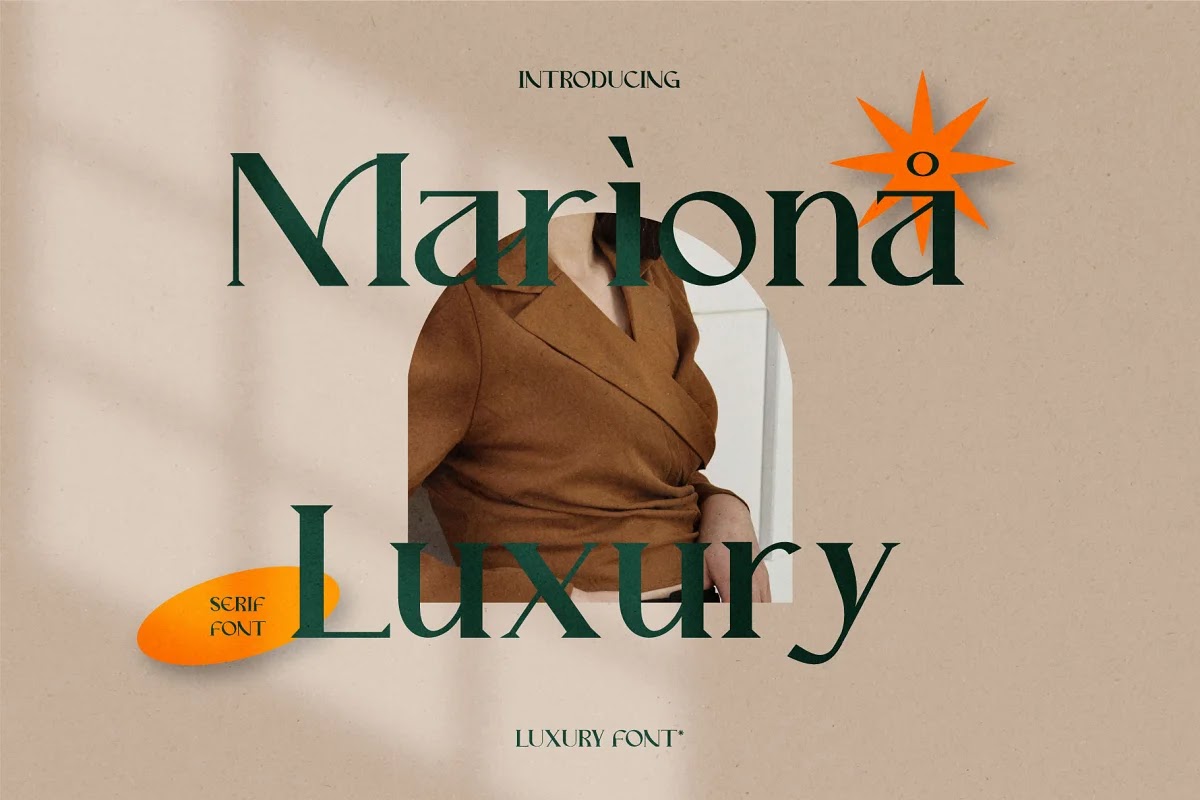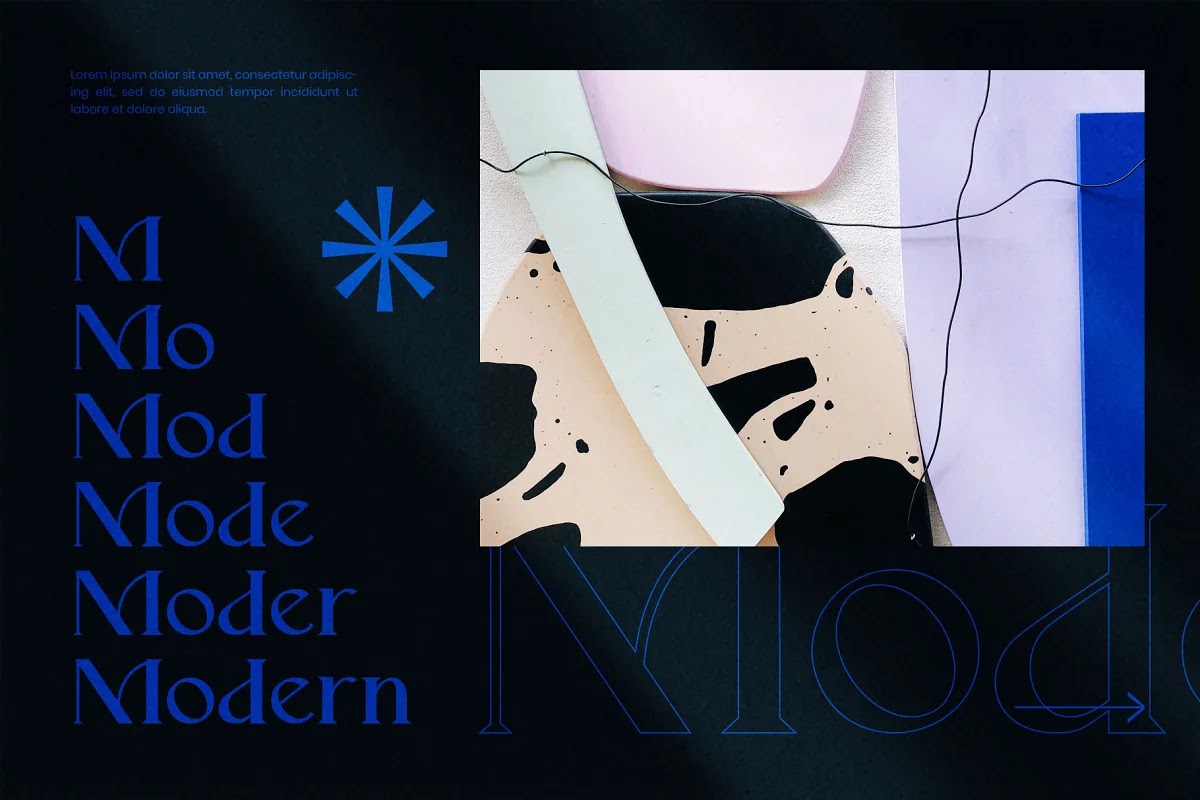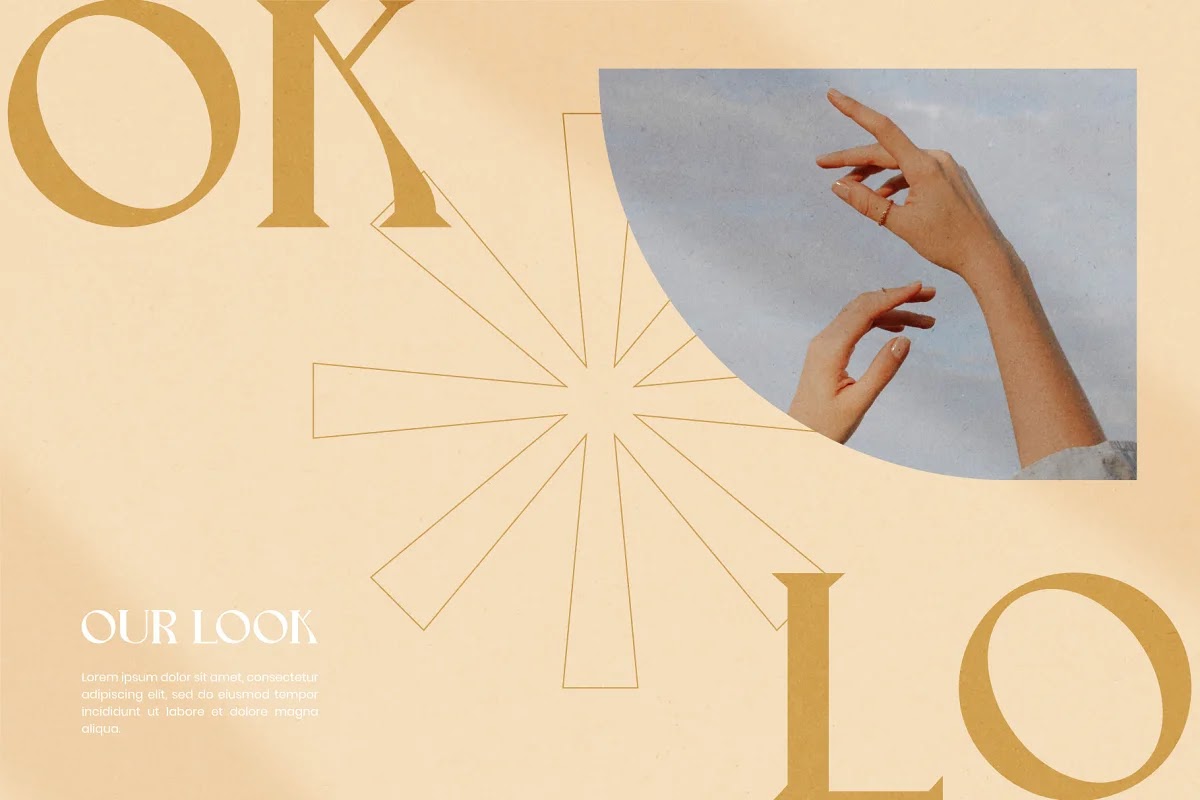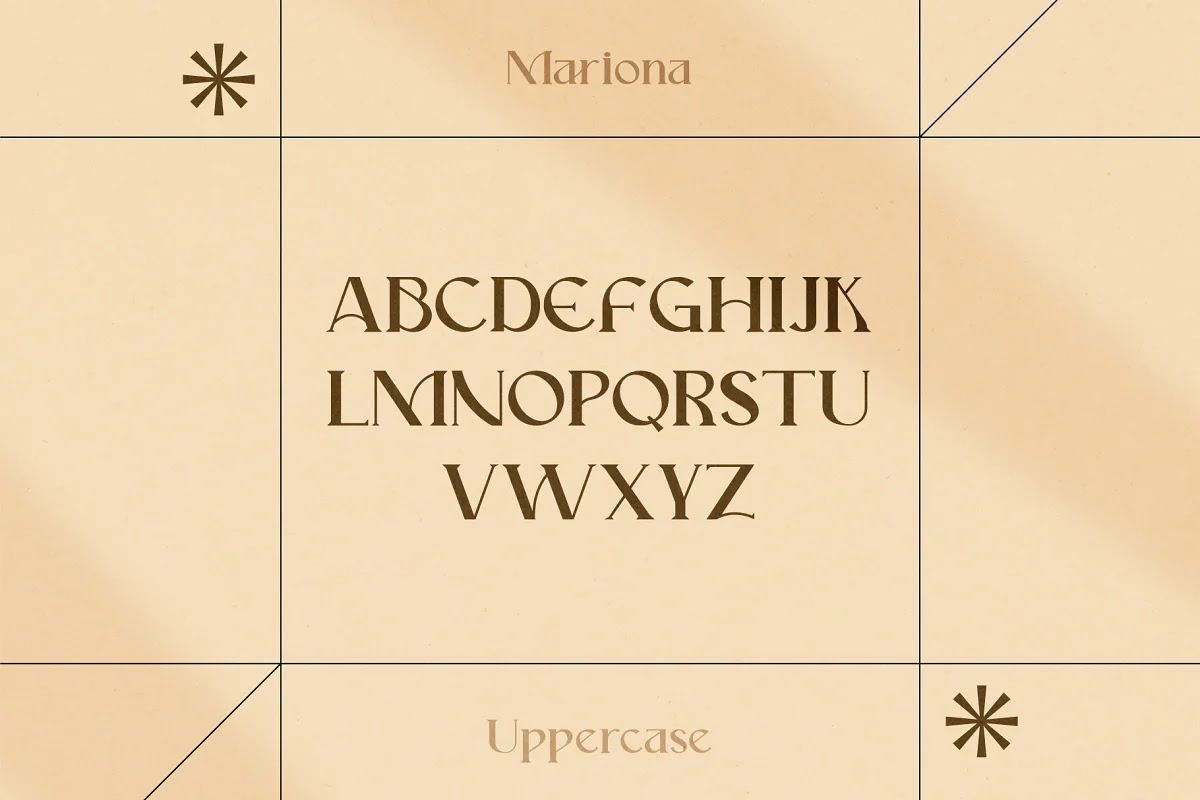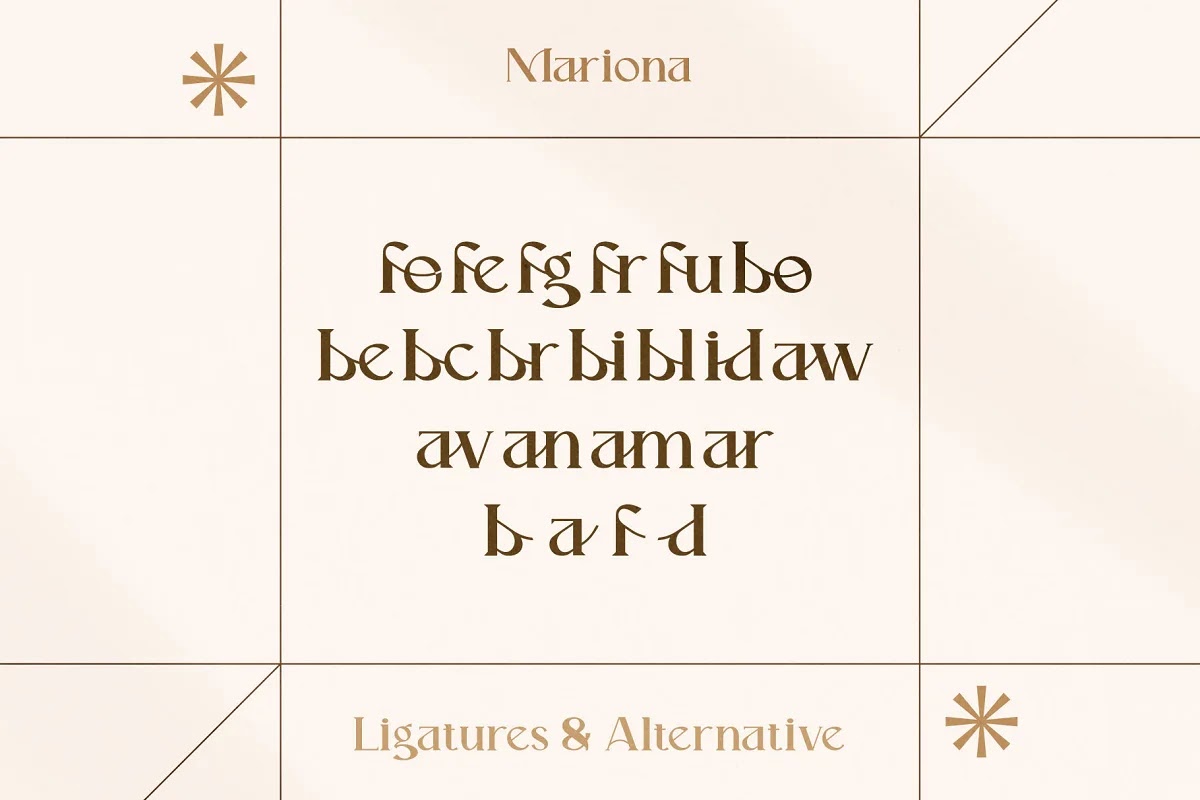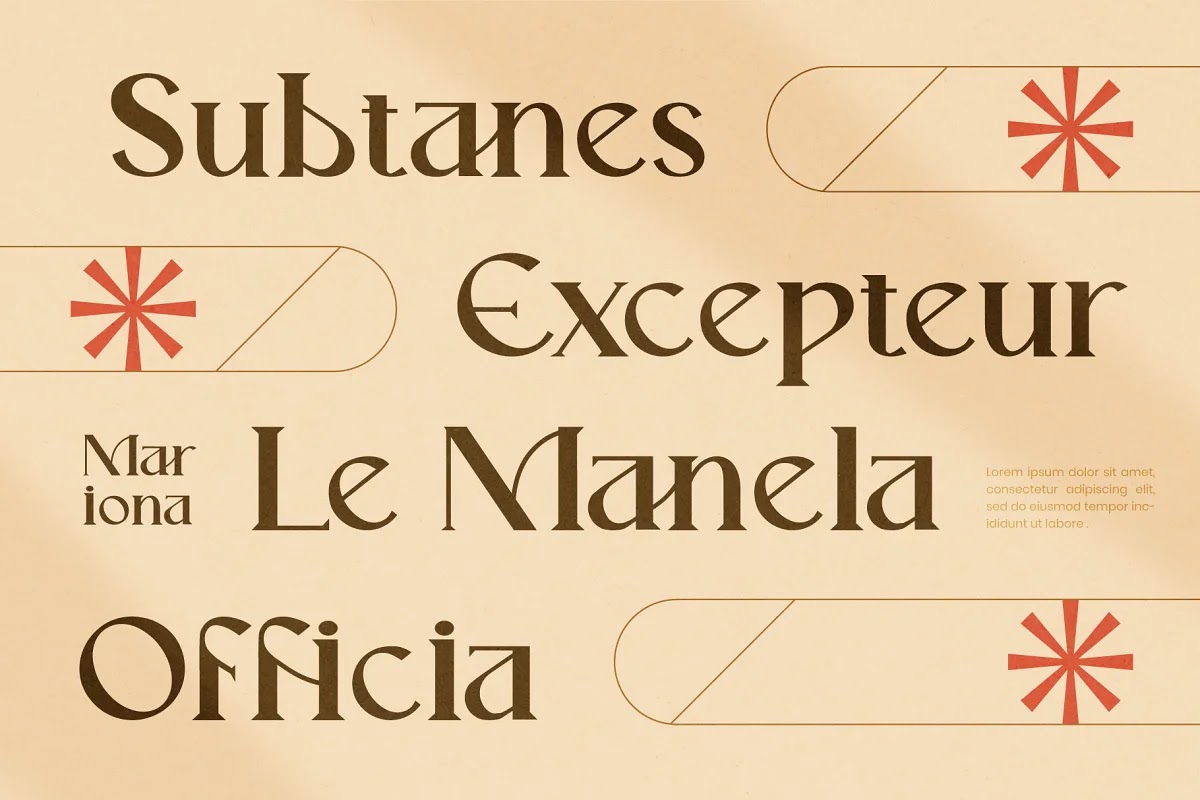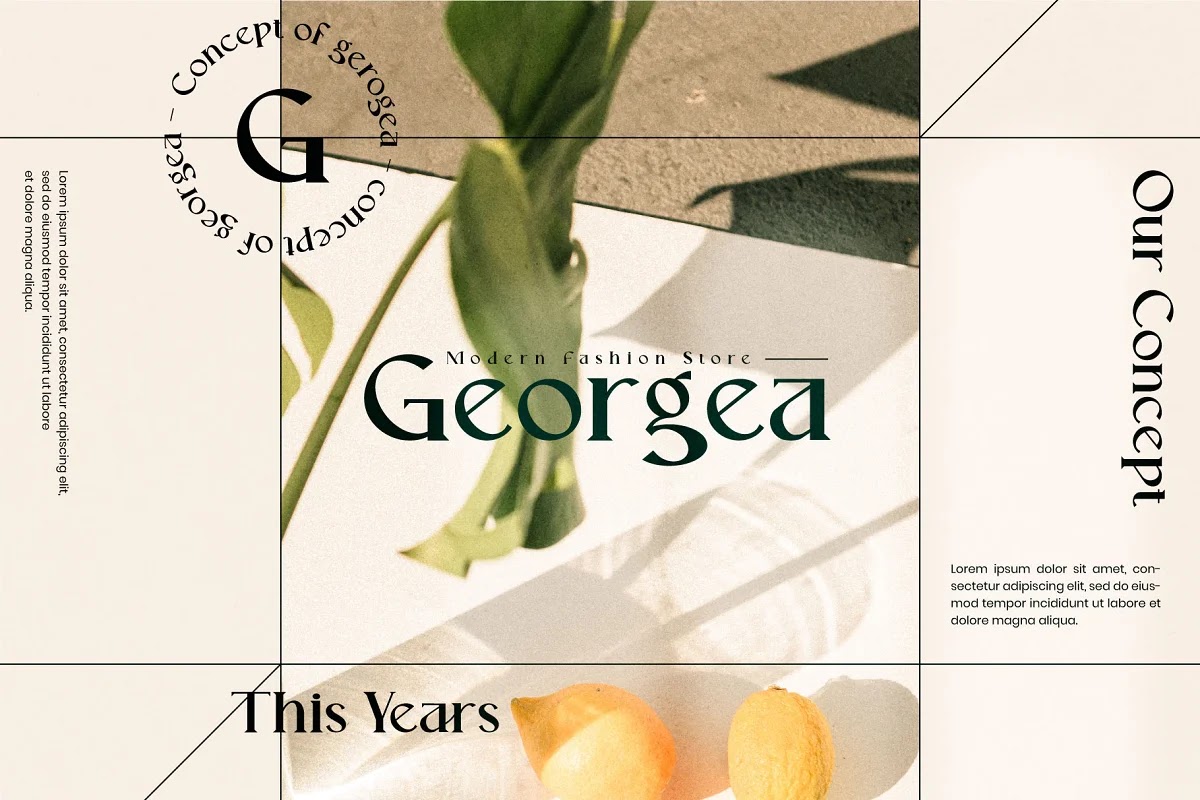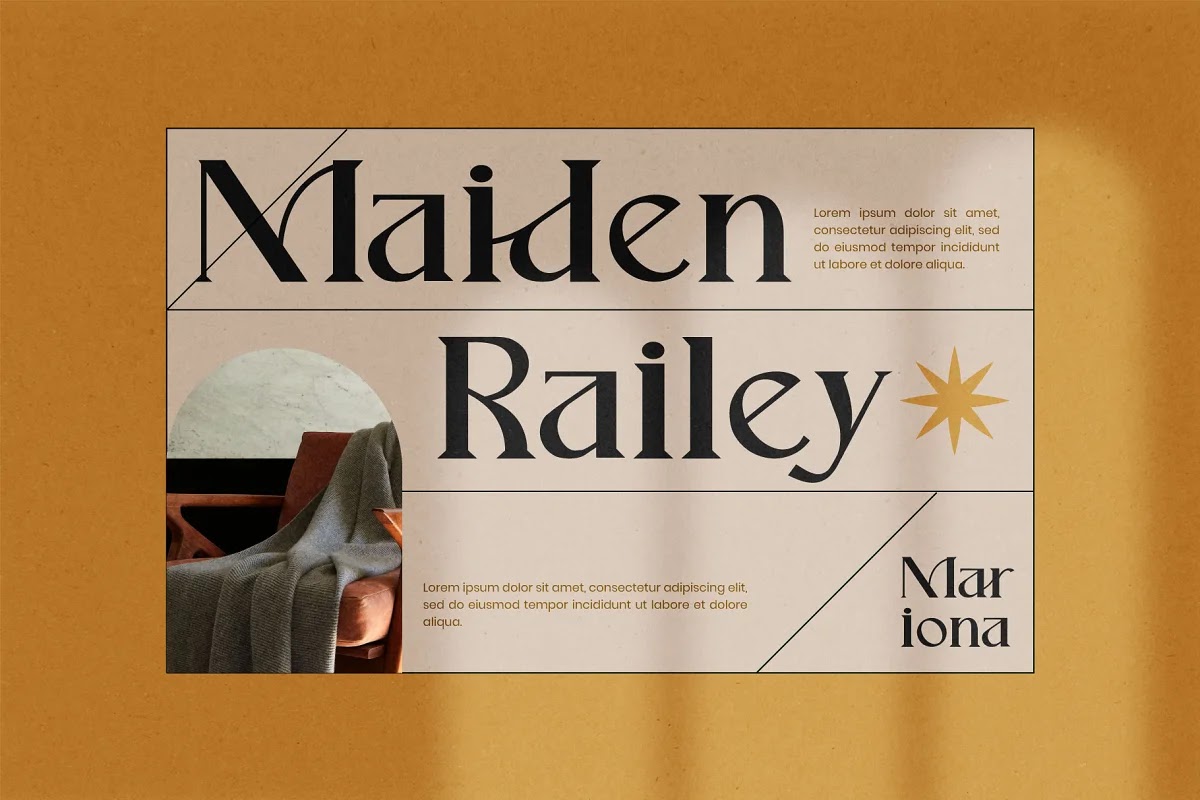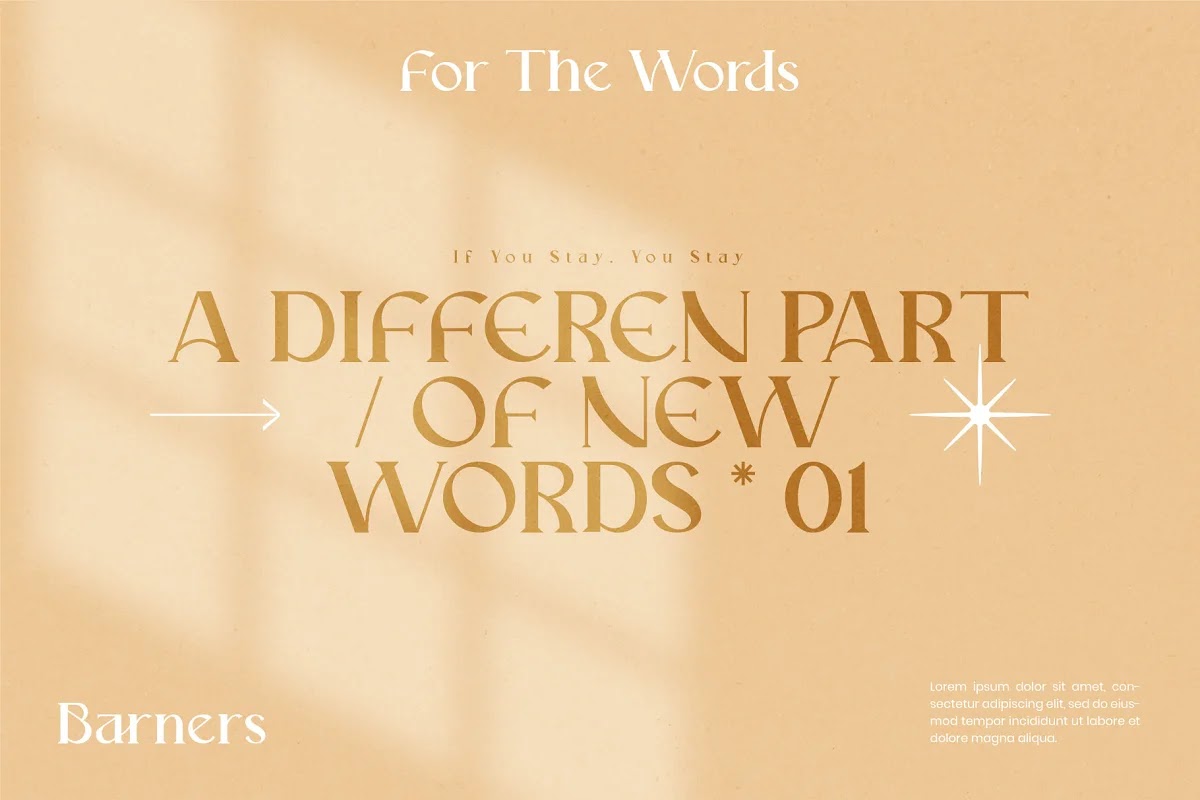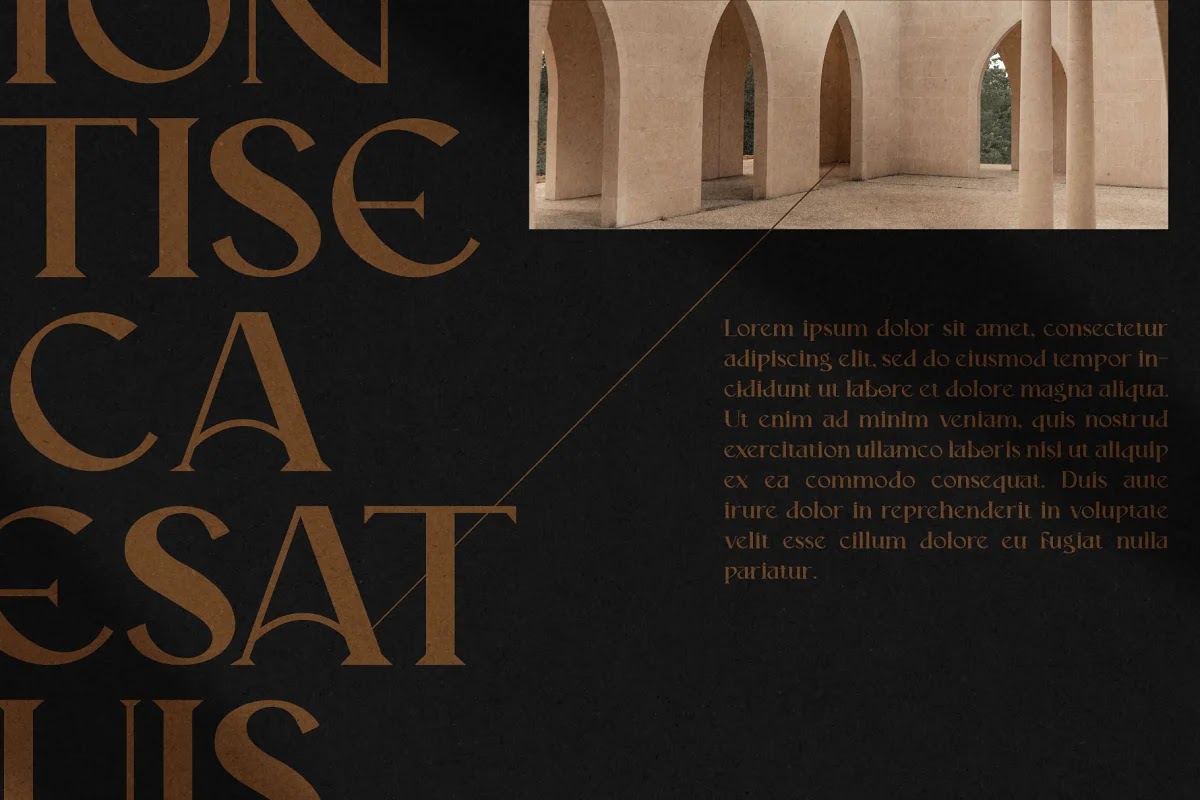
Font Mariona Serif là một font chữ ấn tượng với thiết kế hoàn hảo hoàn toàn phù hợp với nhiều thiết kế như thích hợp cho áp phích, tạp chí, hàng may mặc, tiêu đề phim, bao bì và hơn thế nữa.
Với các nét chữ được thiết kế vuông vức và với 1 chút uốn cong mềm mại tạo ra cảm giác ấn tượng và thẩm mỹ. Font hoàn hảo để sử dụng cho cả văn bản nội dung và các tiêu đề lớn cần sự mới lạ và độc đáo.